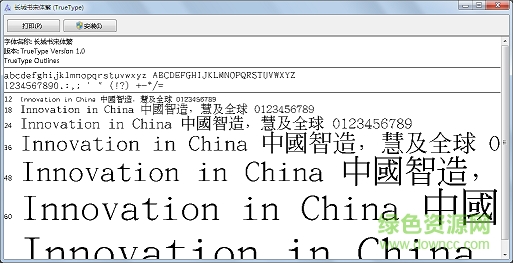
長(zhǎng)城書宋體繁是一款方正的繁體宋體。對(duì)于該字體,可能使用的朋友不是很多,但是還能了解多一種字體的寫法,也是一鍵有趣的事情。喜歡就來綠色資源網(wǎng)下載吧!
應(yīng)用于平面設(shè)計(jì)方面的繁體中文字體。該字體端正大方得體,線條纖細(xì),整體效果非常出色,可廣泛應(yīng)用于平面設(shè)計(jì)、簽名設(shè)計(jì)、廣告設(shè)計(jì)、報(bào)紙雜志、正文標(biāo)題等領(lǐng)域,